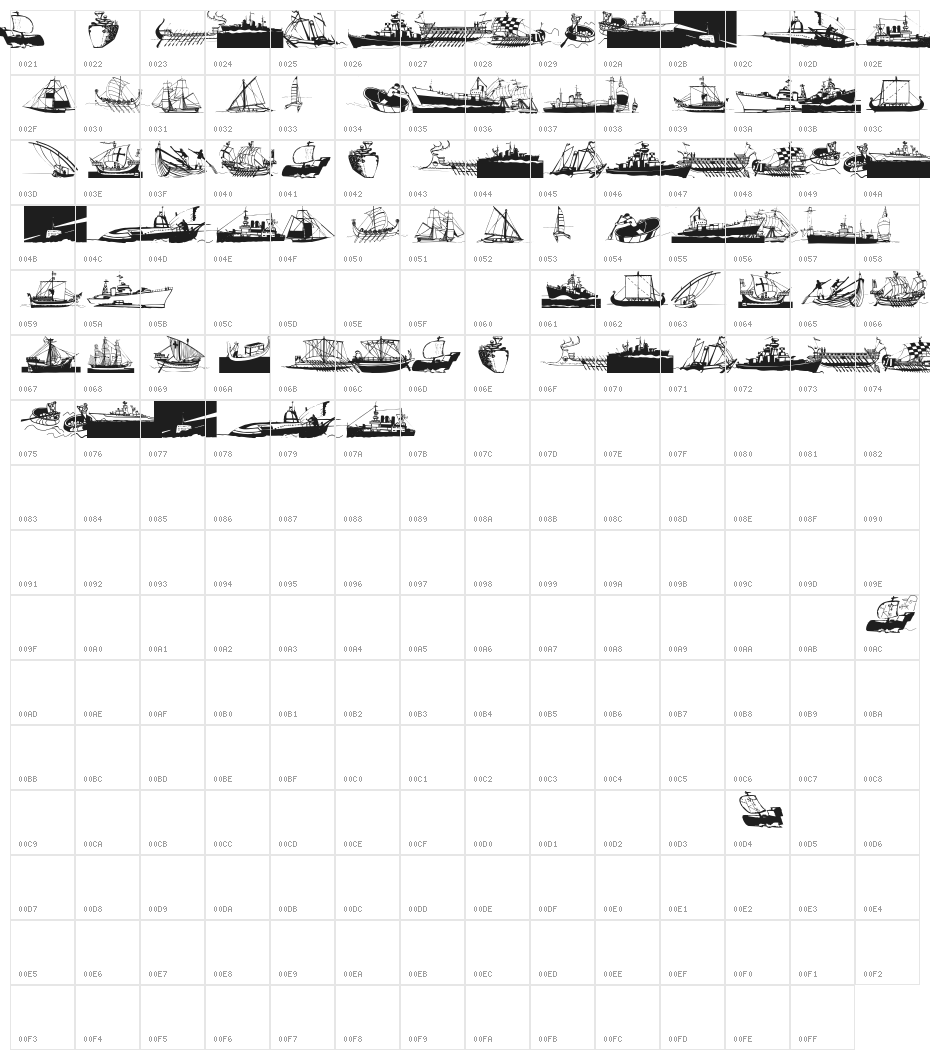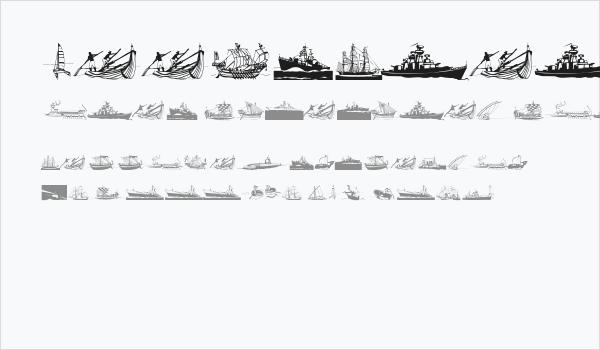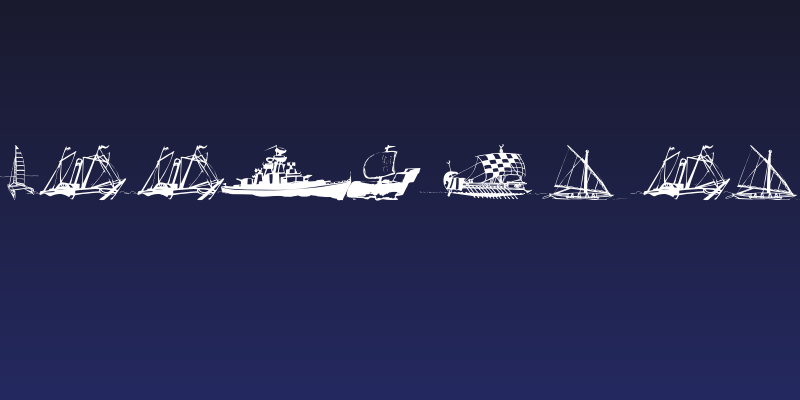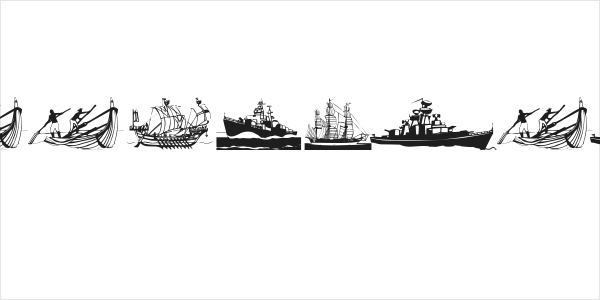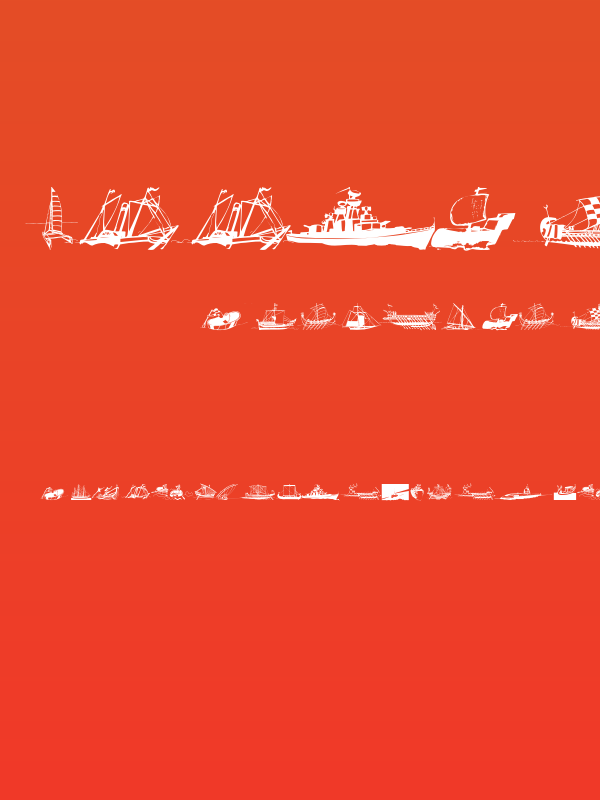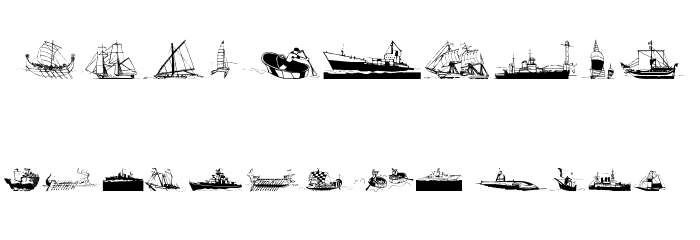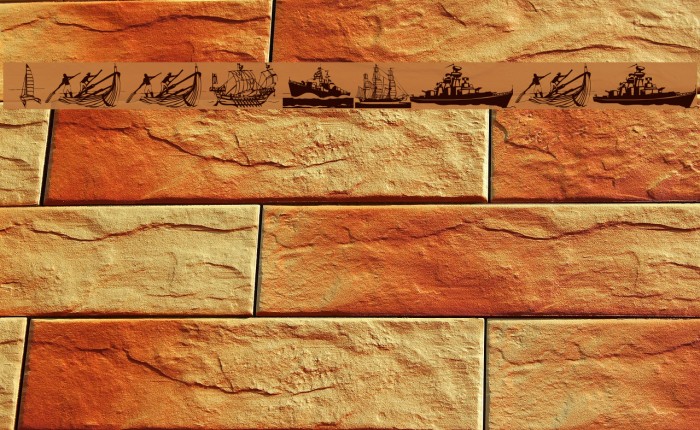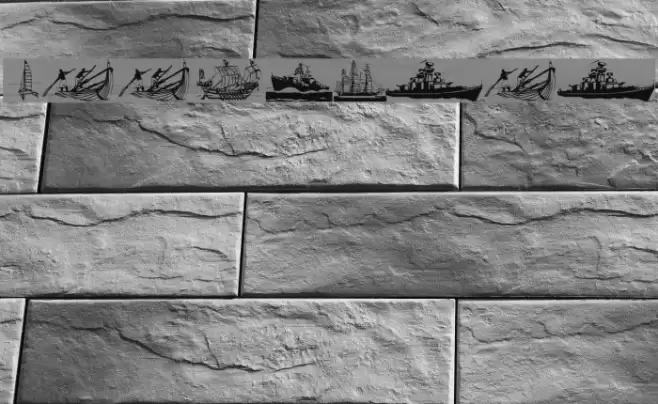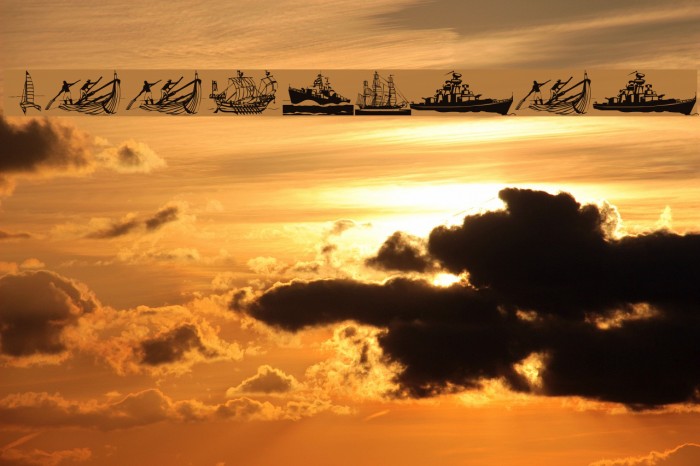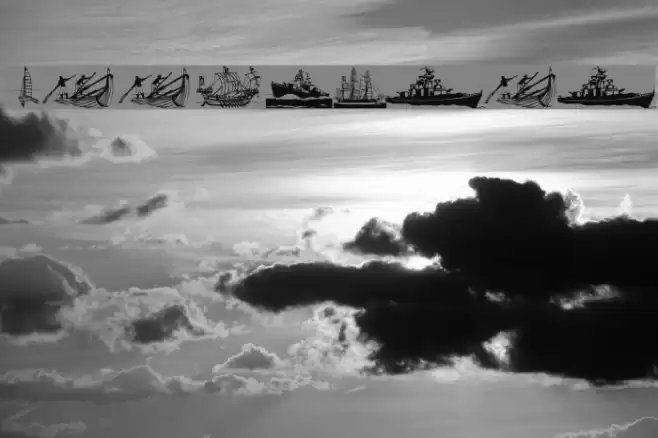
Seefahrer Font
| Estilo geral | Decorative, Nautical, Illustrative |
| Caso de uso | Logos, Headlines, Posters, Themed graphics |
| Projetos propostos | Nautical event posters, themed invitations, maritime museum displays, children's books, educational materials about ships. |